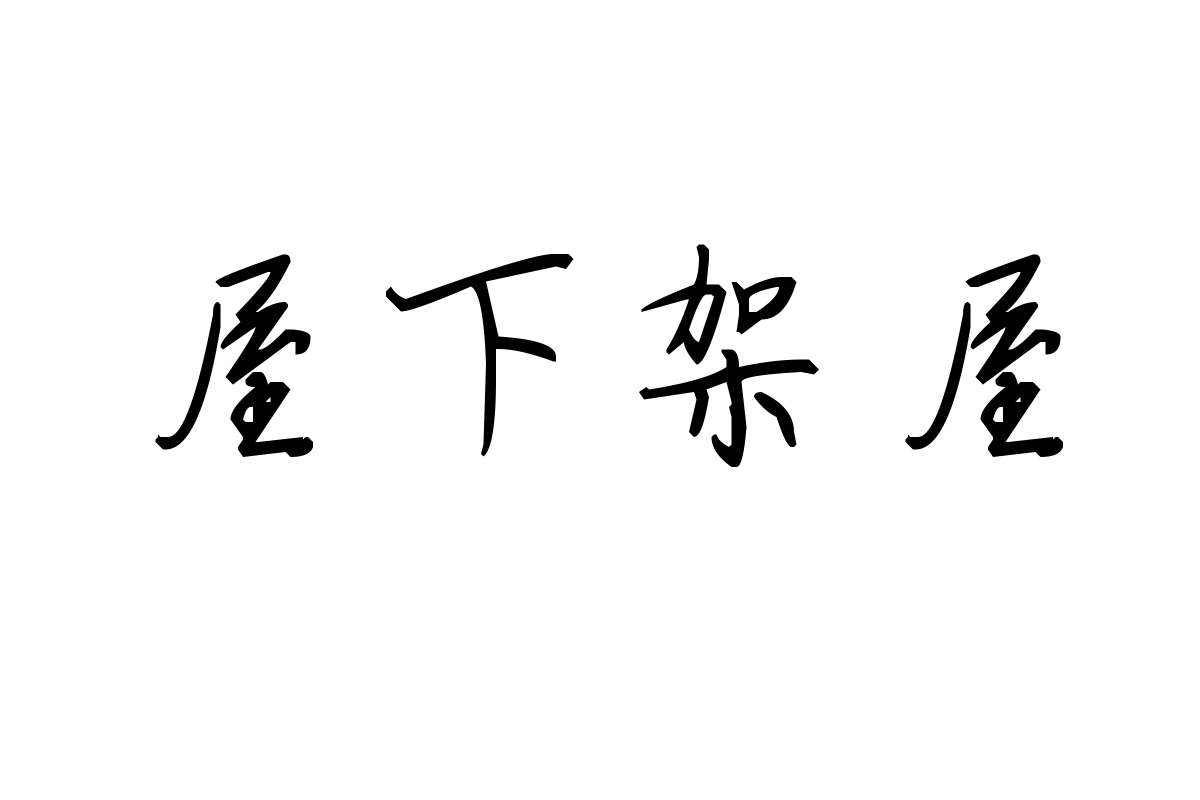
米开水晶之恋是一款具有独特魅力的字体,它以优雅、清新的风格赢得了广大用户的喜爱。该字体采用了独特的手写风格,线条流畅自然,给人一种宁静而舒适的感觉。其字形结构紧凑,笔画粗细适中,既适合用于正式场合的文字展示,也适合用于设计海报、宣传册等。此外,米开水晶之恋还具有很好的可读性,无论是在哪种应用场景下都能保证文字的清晰度和易读性。总之,米开水晶之恋是一款非常实用的字体,值得您尝试使用。